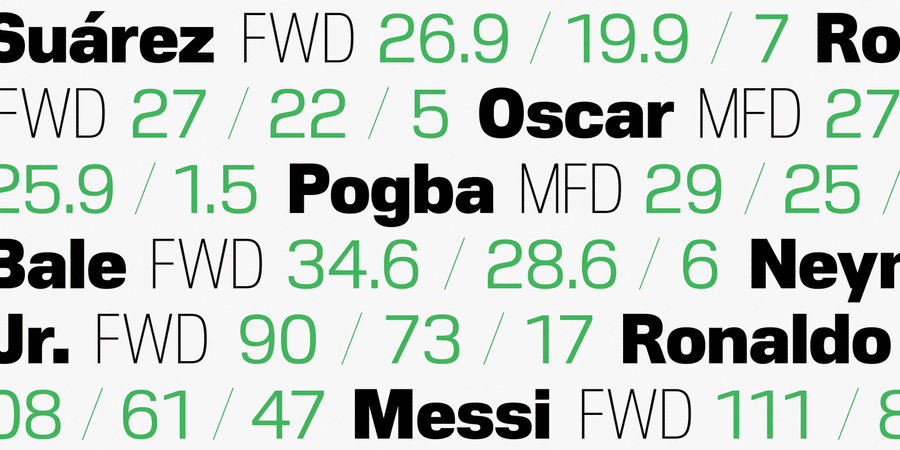
Nuber Next – це сучасний геометричний гротеск, створений під впливом популярних неогротесків 1950-х років, включно з Helvetica та Univers. Гарнітура ретельно перероблена з оригінального сімейства Nuber. Поліпшено форми літер, додано систему гнучкої ширини, здатну обробляти ширший спектр друкарських завдань. Сімейство включає 90 накреслень: дев'ять варіантів жирності та п'ять варіантів ширини з відповідними курсивами. Кожне накреслення містить 750 гліфів і функції Opentype: сім комплектів цифр, дроби, форми з урахуванням регістру, стилістичні альтернативи, лігатури, розширені грошові символи. Мовна підтримка охоплює західну, південну та центральну Європу, кирилицю, включно з азіатською та болгарською. Шрифт розробив Джонатан Хілл у 2018-2020 роках. Nuber Next™ є торговою маркою компанії The Northern Block.
90 накреслень
Асоціації з сімейством шрифтів Nuber NextОсобистість і характер гарнітури:
делікатний, чистий, легкий, худий, прохолодний, тонкий, сучасний, рівний, якісний, невагомий, прозорий, міський, чіткий, інтимний, крихкий, повітряний, скляний, дротяний, статичний, стрункий, високий, свіжий, економний, економічний, зрозумілий, діловий, космополітичний, ненав'язливий, технічний, прямий, глобалізований, глобалістічний, монотонний, прагматичний, практичний, твердий, невиразний, точний, серйозний, щільний, переконливий, солідний, сильний, важливий, строковий, швидкий, наполегливий, рішучий, спортивний, ясний, мінімалістичний, лаконічний, спокійний, формальний, розумний, важкий, значний, стійкий, модний, динамічний, різкий, логічний, приємний, доступний, комфортний, Простий, зручний, стандартний, впевнений, мотивуючий, потужний, помітний, яскравий, активний, амбітний, міцний, мужній, кондовий, суворий, добротний, монументальний, гучний, сміливий, брутальний, надійний, індустріальний, техногенний, урбаністичний, авторитетний, крутий, залізничний, самостійний, відповідальний, західний, обов'язковий, гострий, гоночний, стабільний, швидкісний, інженерний, креслярський, енергійний, кінематографічний, тісний, нахабний
дієта, гігієна, дизайн, Місто, чистота, хмарочос, кінотеатр, цигарки, бізнес, торгівля, магазин, реклама, комп'ютерна гра, кіно, Футбол, прапор, спорт, медицина, будматеріали, вантажоперевезення, інструмент, вантажівка, далекобійник, логістика, туалетна вода, інновації, перукарня, парфумерія, лосьйон, шампунь, суспільство, транспорт, аеропорт, метро, ліки, коворкінг, наука, хімія, фізика, вода, автобус, аптека, новини, політика, автомобіль, авто, Доставка, техніка, будівництво, ремонт, машинобудування, завод, промисловість, верстат, тренажери, сейф, екскаватор, металургія, порт, двигун, урбаністика, електростанція, енергетика, мотор, прес, вагон, залізниця, паливо, формула 1, тачки, авіація, літак, шолом, мода, прилад, одяг, небо, взуття, інженер, поліція, гонки, ралі, гра, швидкість Гарнітура має ознаки стилів: